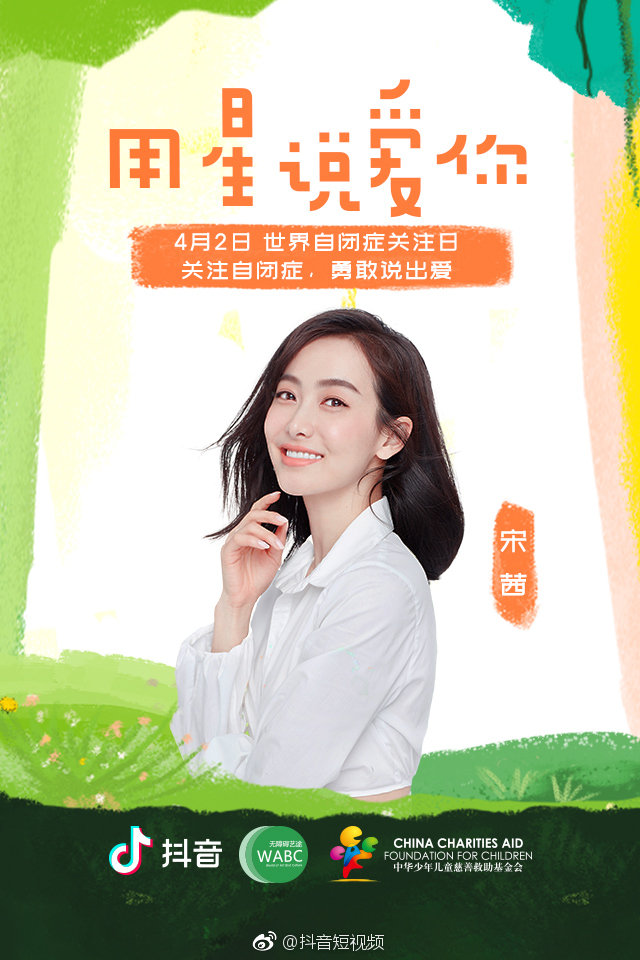
方正仙阵体
张玲丽,广煜
仙阵体是基于方正基础像素体的再创造,重设了笔画结构,撇捺点进行了1/4圆的圆弧设计,折钩部分设计成圆角,统一字体风格的同时更添趣味性情感,较之更易识别、更具易读性。仙阵体的每个字有其统一的最低基准线,而每字的海拔不尽相同,字宽也非一样,每个字有着其独特的韵味,排成的文章整齐的同时又极具韵律感,犹如阵列,有音符跳跃般的节奏感。如果您的产品是活泼可爱有个性的,那么试试选择这款字吧! 适用范围:字形适用于建筑、产品类设计的视觉设计,以及时尚类品牌的广告和包装的设计。